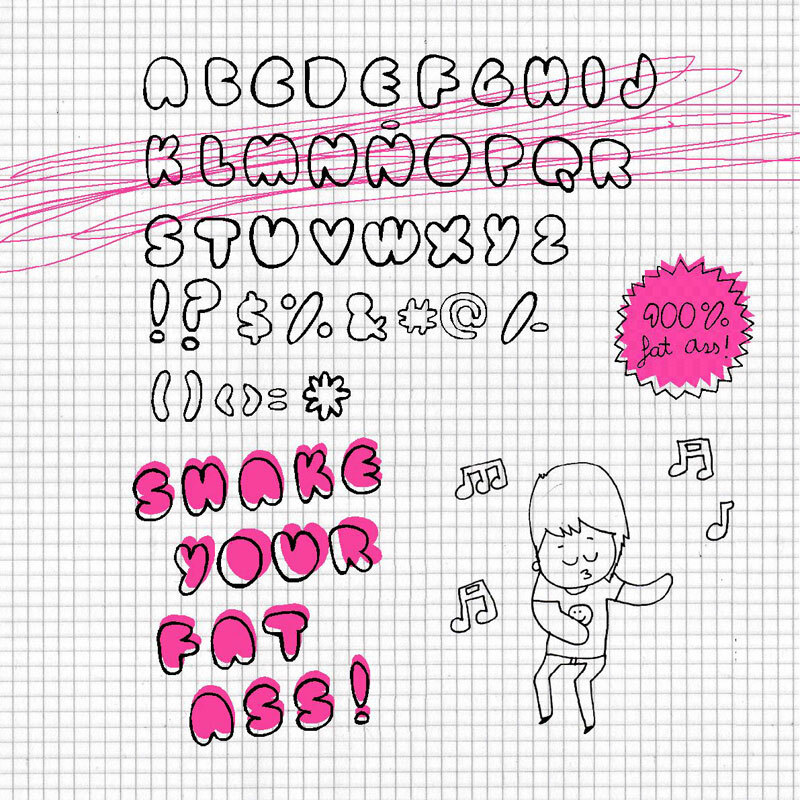
Fat Ass Outline, bezplatné komiksové obrysové písmo, sází na efekt nafouknutých bublinových písmen s hravým, ručně kresleným nádechem. Písmena působí měkce, baculatě a lehce nepravidelně; silné obrysy a masivní tvary dodávají celému písmu výrazný kreslený styl.
Skvěle se hodí na plakáty, grafiku pro dětské akce, obaly na snacky, komiksové titulky, úvodní karty a velké monogramy, kde je volné písmo s takovým objemem a pružností přesně to pravé. Protože jsou velká písmena tak oteklá a jednoduchá, nejlépe vynikne v krátkých slovech a nadpisech, které nechají tyto buclaté siluety mluvit za sebe.